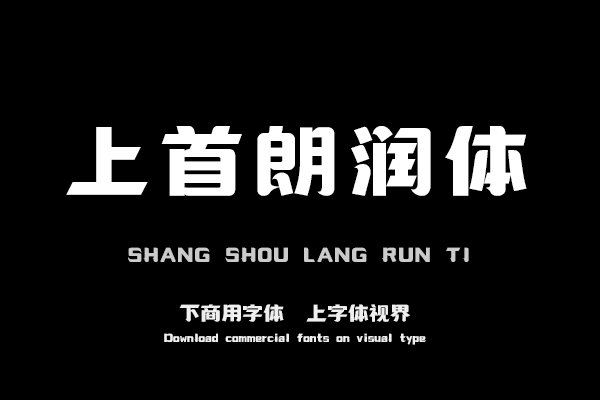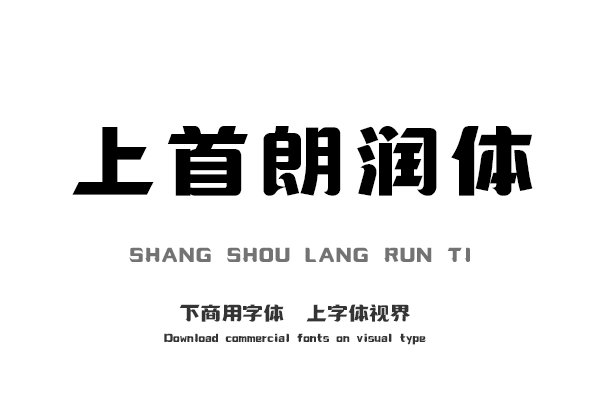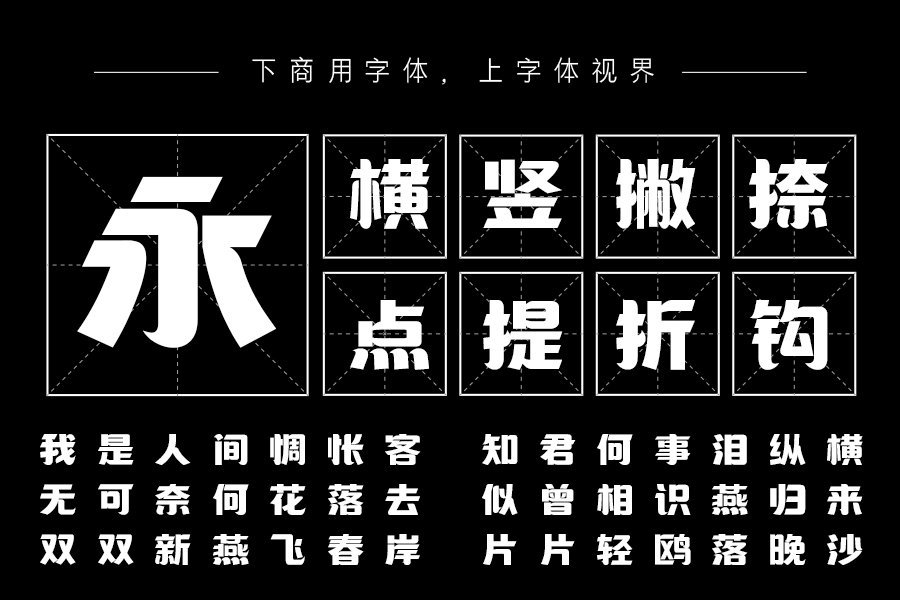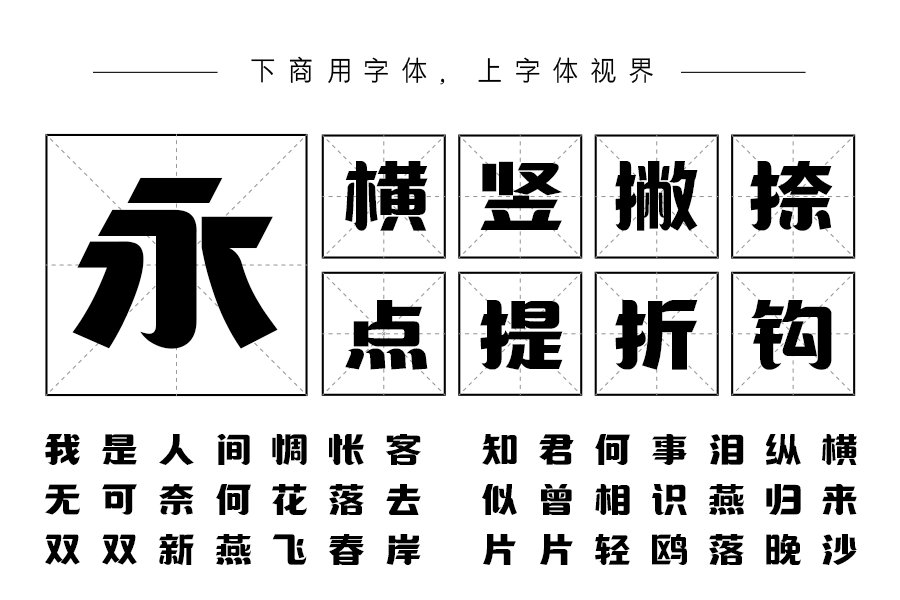
上首朗润体,简体中文约6763字,字体笔画刚柔相济端庄优雅,字体一橫笔两头有切角,使字体显得刚硬,随性而有个性,字体刚中带柔,装饰性刚强,适用于搭配标志、广告标......购买须知:“下载服务费”与“字体VIP”所获得字体 仅用于个人非商用, 商用请联系付费授权。本字体为电脑用字,手机没有root权限不支持直接手机换字(手机如何root,请自行百度搜索教程)。购买前请先 了解清楚后再付款 ,字体为虚拟产品无法回收 一旦购买不支持退款。